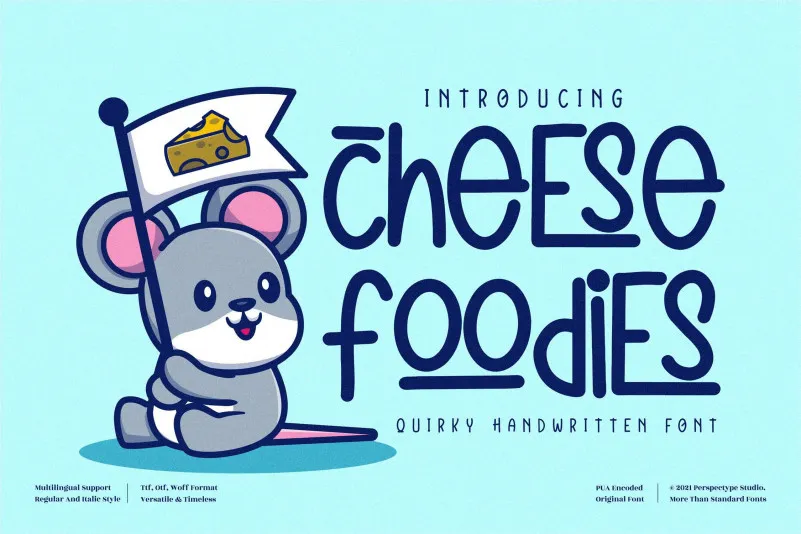
Cheese Foodies Font – Fonte Grátis
Cheese Foodies Font
A fonte “Cheese Foodies Font” é uma escolha perfeita para aqueles que procuram algo simples e divertido para suas criações gráficas. Desenvolvida pela perspectype, ela adota um estilo handwritten leve e um pouco engraçado. É uma font ideal tanto para projetos relacionados a personagens animados ou jogos infantis, quanto para qualquer outro projeto que precise de um toque encantador e suave. Com “Cheese Foodies Font”, seu trabalho ganhará vida e personalidade com essa fonte única e charmosa. Atrairá os olhos por onde quer que ela seja aplicada, tornando seus designs uma verdadeira delícia para a vista, desde cartões de aniversário até banners de lojas infantis. Experimente adicionar um toque especial à sua próxima criação com essa font leve e divertida.